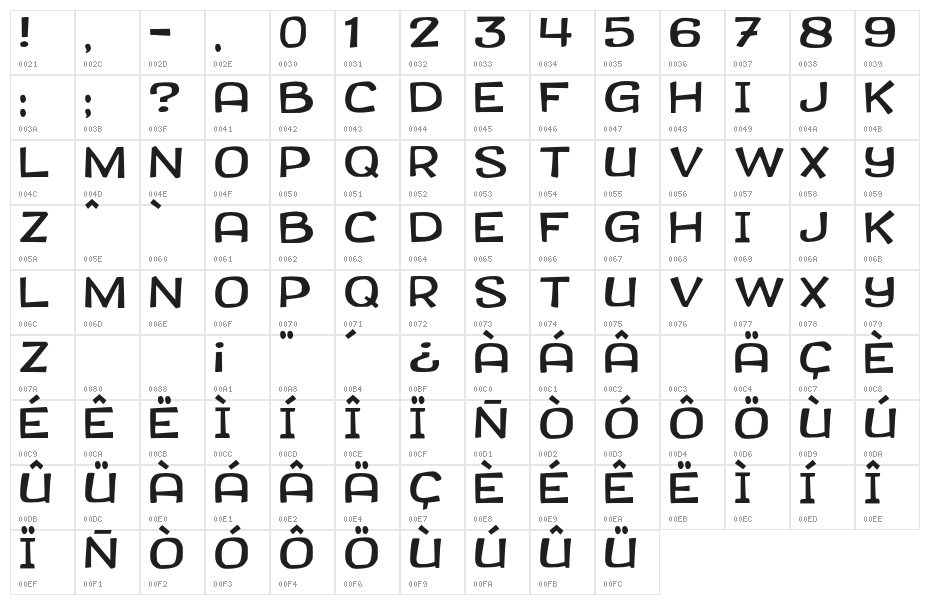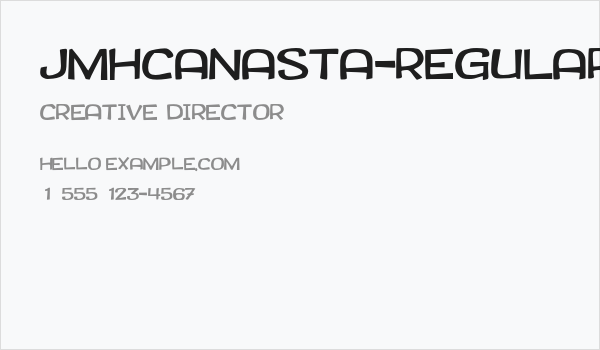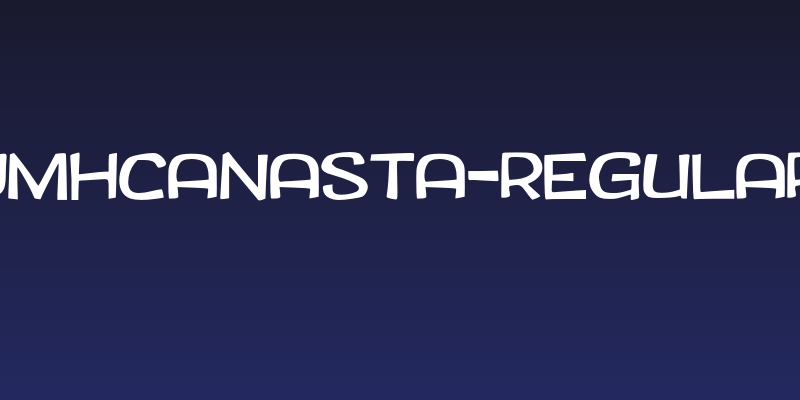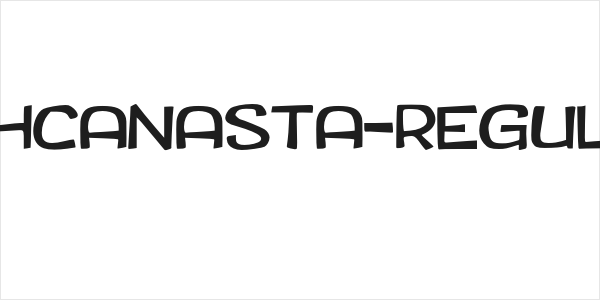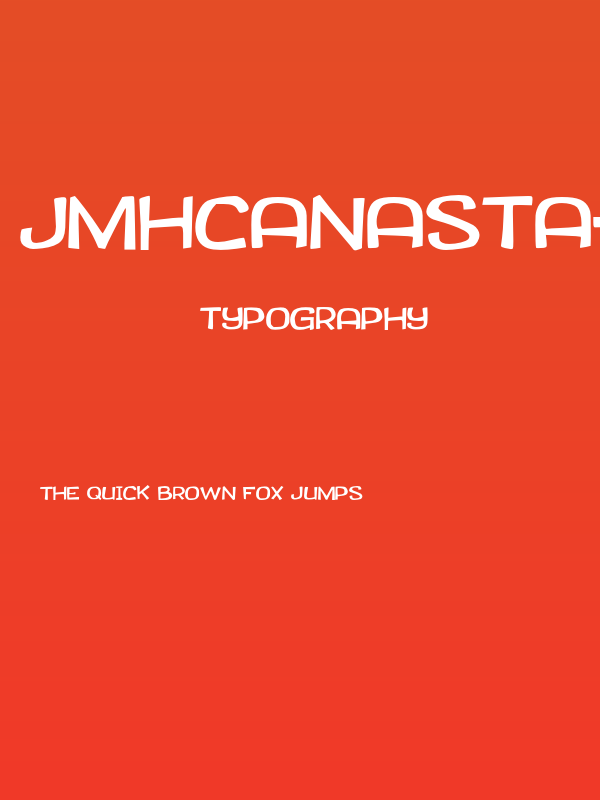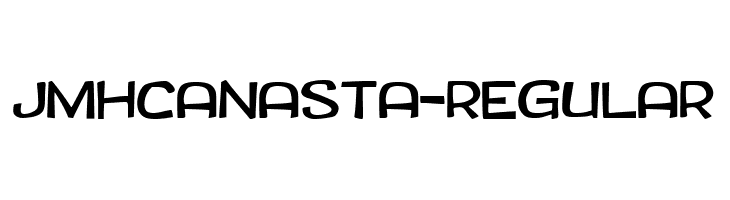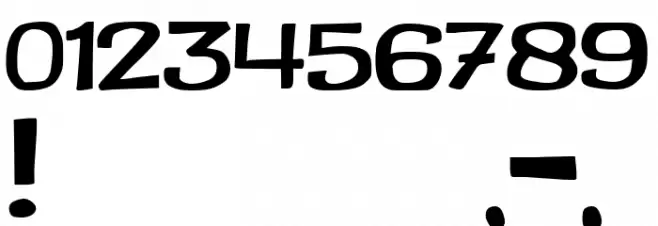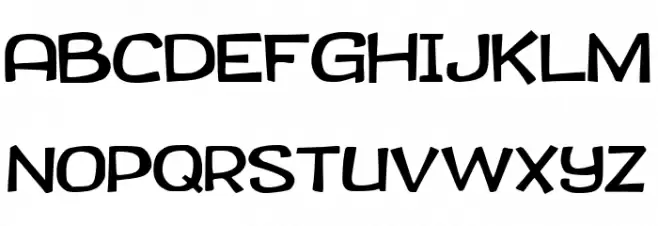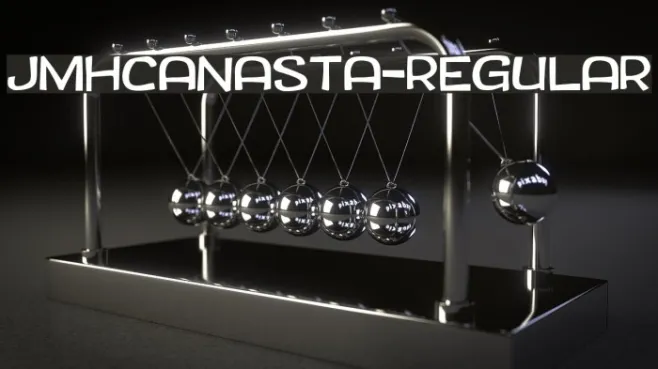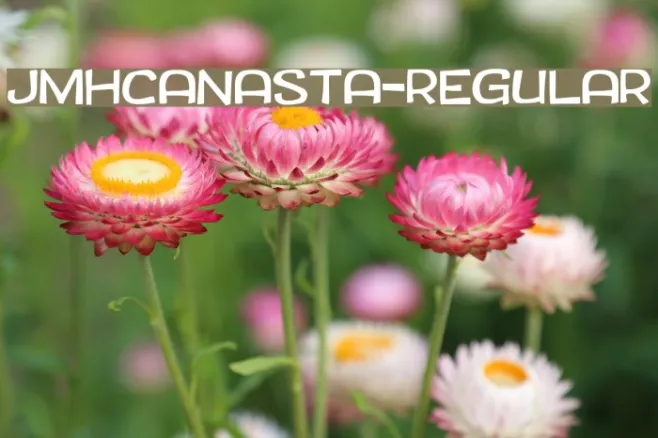
JMHCANASTA-Regular Font
| Style général | Playful, Creative |
| Projets proposés | Ideal for children's books, comic strips, playful branding, and creative posters. |